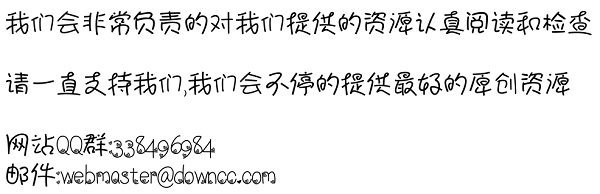
飄逸瀟灑字體是一款造型精簡、筆畫活潑的可愛字體,中文漢字打破規(guī)整的設計,充滿了童真童趣的藝術效果,英文字母和數(shù)字中增加了心形點綴,給人舒適的視覺呈現(xiàn),喜歡的朋友就來綠色資源網(wǎng)下載體驗吧!
飄逸瀟灑體,字如其名,是收錄的最早的手寫字體,兼具飄逸和瀟灑的運維,也有十分獨特的童稚運維,可以運用在平面設計、藝術設計等領域。